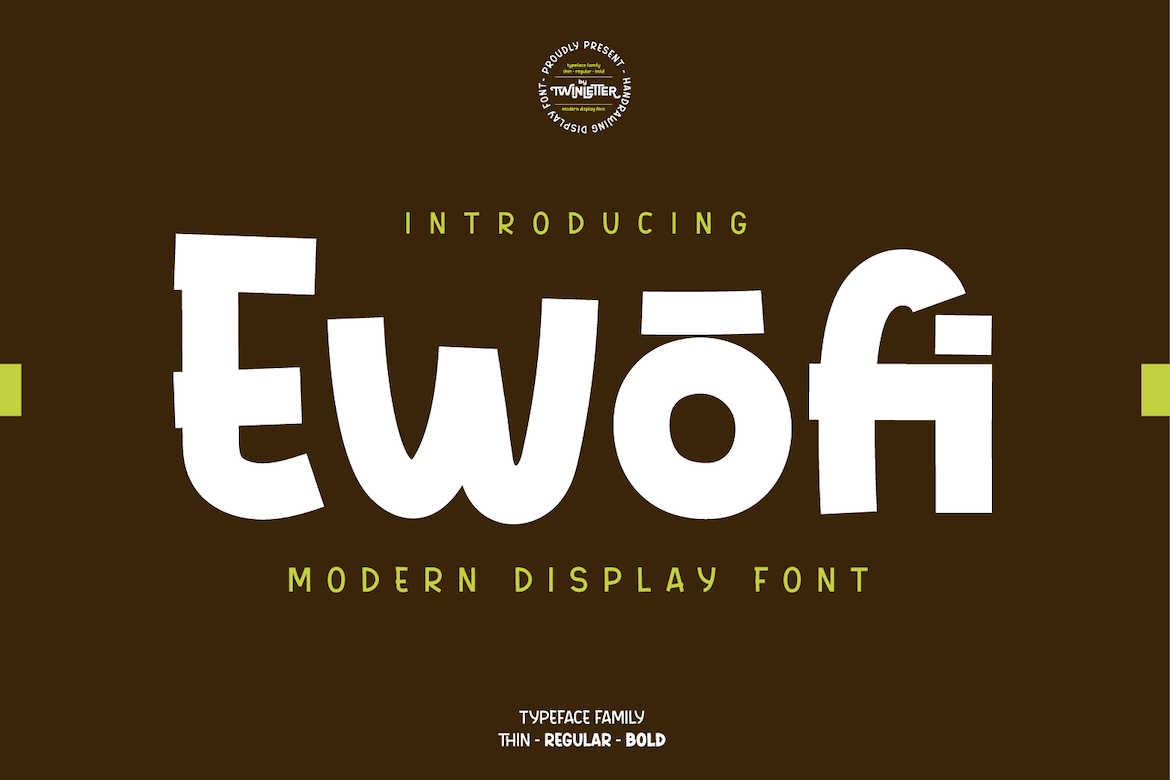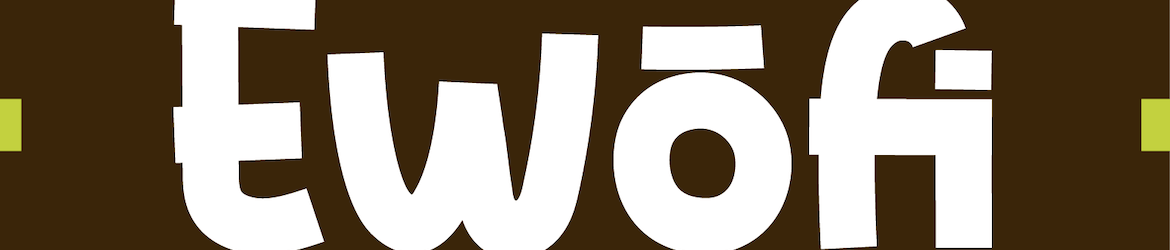
A fonte ‘Ewofi Font’ é uma escolha ótima para designers que desejam adicionar um toque moderno e chamativo a seus projetos. Embora seja designada como um tipo de exibição, que geralmente se destina a uso em materiais gráficos visuais mais impactantes ou publicitários, esta fonte é tão original quanto intrigante. Seu estilo é carregado e contorneado com uma caligrafia moderna, o que permite tornar qualquer projeto onde ela é usada realmente chamativo. Além disso, a característica ‘quirkiness’ (um termo um pouco enigmático em inglês), ou seja, um toque peculiar, dá ao design um charme único e inovador. Não importa o tamanho, a cor ou o contexto de utilização da fonte, ela sempre terá seu próprio espaço, tornando-a perfeitamente adequada para uso em banners publicitários, logos corporativos ou qualquer projeto que busque destacações visuais notáveis.